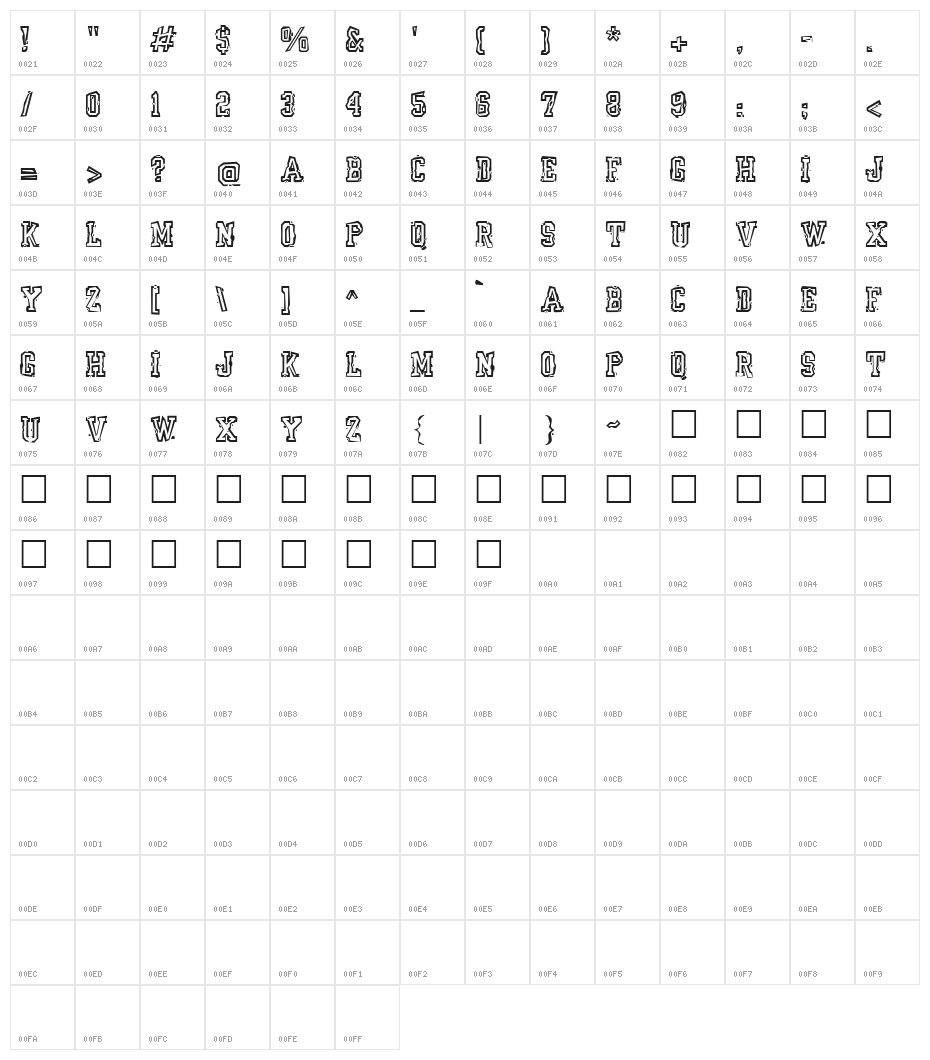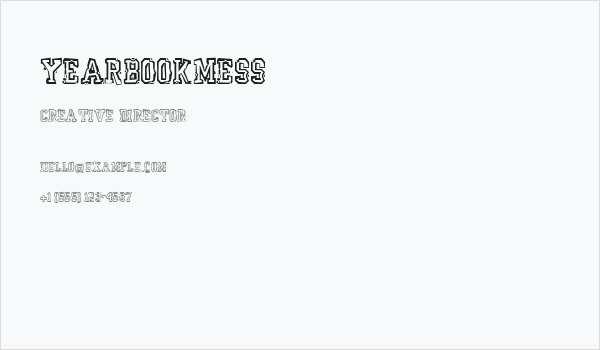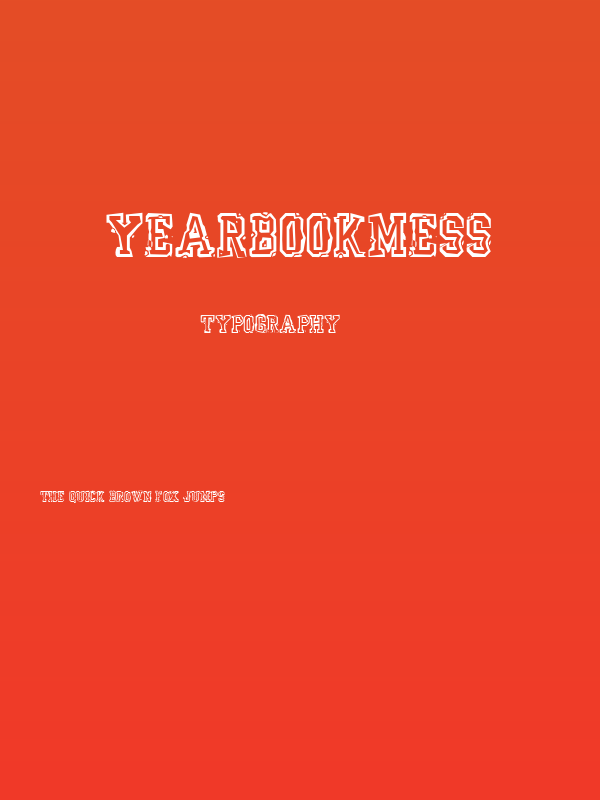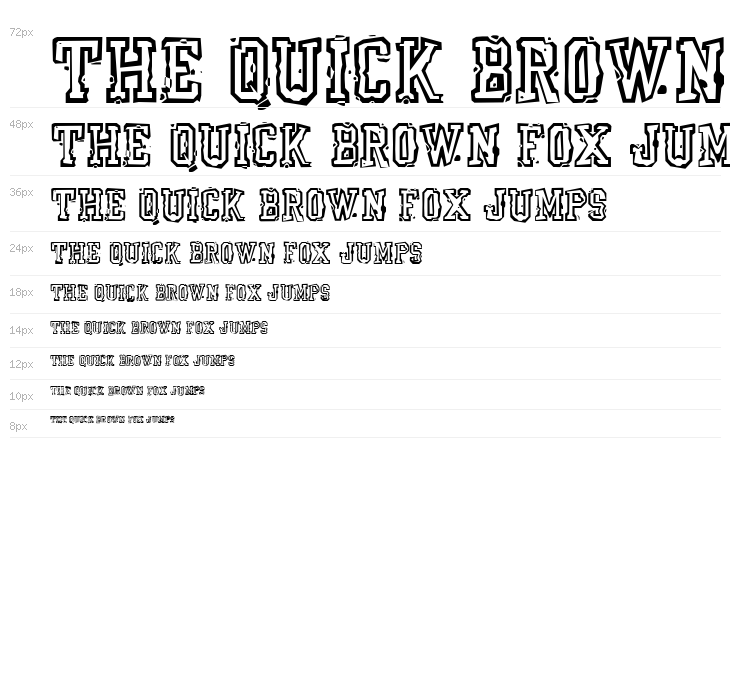
YearBookMess Font
| Stile generale | Vintage, Decorative |
| Progetti proposti | Ideal for poster designs, album covers, vintage-themed projects, and any creative work that requires a bold, standout typeface. |